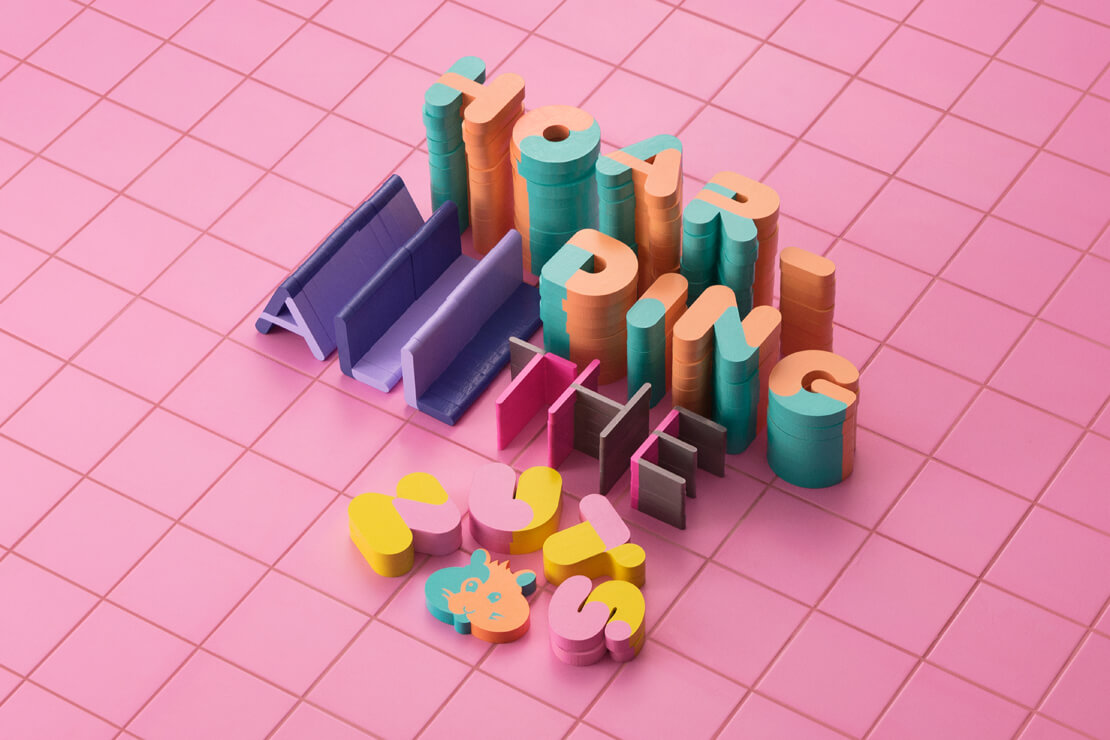
Variable-Color-Font »Hamster« von Fontwerk
Die neue Schriftfamilie, die bei Fontwerk in Berlin erschienen ist, gibt sich fröhlich und farbenfroh. Der Variable-Color-Font von Joe Stitzlein bietet viele Spielereien, Dingbats und natürlich auch Hamster.
Für seine Schrift ließ sich der Designer vom zweifarbigen Charme der Haustiere seiner Freunde aus der Kindheit und der Behausungen der Nagetiere inspirieren.
Unter Verwendung der röhrenförmigen Form dieser sogenannten Habitrails ist die Display-Schrift Hamster entstanden. Sie bietet abgerundete Enden und fette Schriftschnitte, die an die charakteristischen Pausbäckchen der Nager erinnern sollen.
Die schlankeren Schnitte geben sich weniger verspielt und eignen sich laut Fontwerk zum Einsatz in Logos, für junge Fashion-Brands, Lebensmittelmarken und mehr.
Hamster ist in 10 Farbvarianten erhältlich. Nutzerinnen und Nutzer können die Farbgebung aber auch individuell bestimmen, um beispielsweise die speziellen Farben einer Marke, eines Events oder einer TV-Serie widerzuspiegeln.